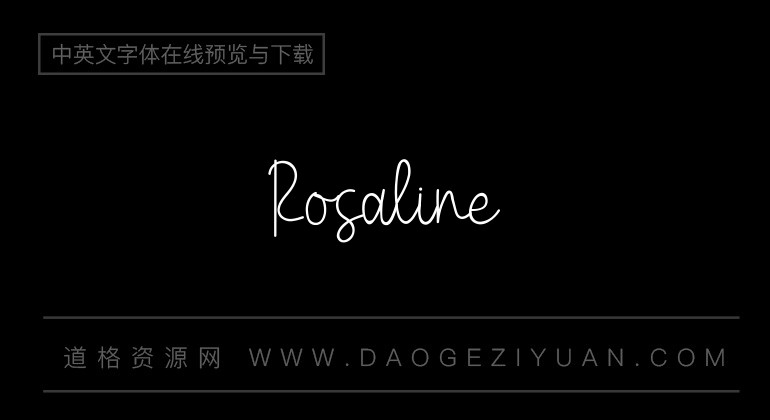
Rosaline
Rosaline是一款由Fontfabric创作的欧洲字体,它拥有简洁而优雅的外观,是一款抽象风格的字体。它有着清晰的曲线,非常适合用于logo和标题的设计。它的字体特性使它适合用于品牌标识、网站标题、印刷品、海报等等。此外,它还具有多种字体格式,包括OTF,TTF,WOFF和WOFF2,可以让您轻松地设计出专业的设计作品。
Rosaline是一款非常不错的手写艺术字体,具有很好的视觉感,适合于文化类的宣传设计、商业类品牌的广告和产品包装设计以及个性化文字排版等较多场景。